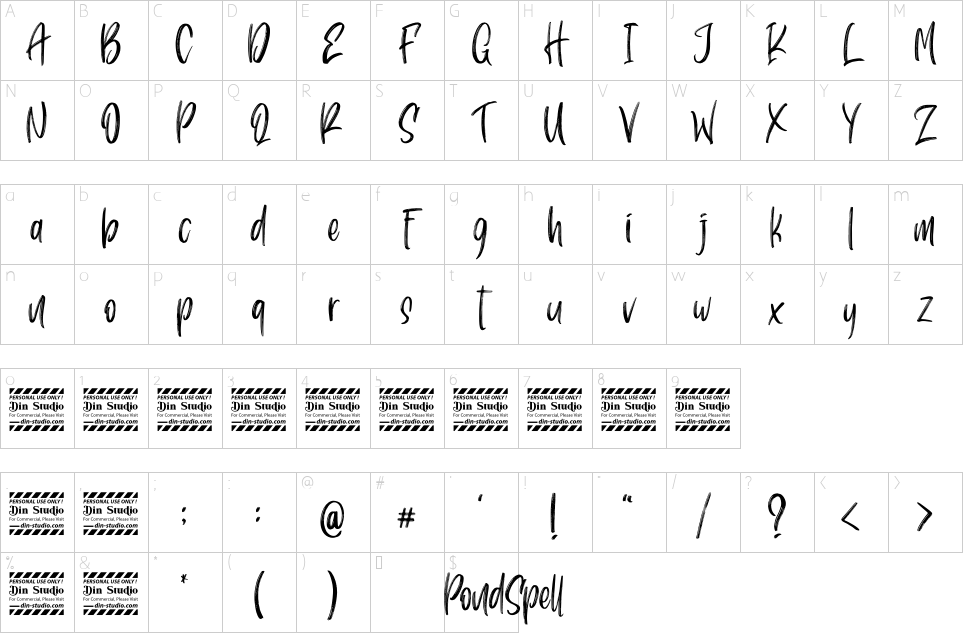
Descubra a beleza de Pondspell, uma fonte grátis disponível tanto para Windows quanto para Mac. Desenhada pelo Din Studio, Pondspell é mais do que um recurso para estilizar seu próximo projeto de design. Suas formas elegantes e sua tipografia cuidadosamente desenvolvida podem tornar qualquer trabalho em design de arte mais envolvente. Esta fonte oferece um toque único e inspirador, perfeito para aqueles que buscam uma adição fresca e versátil à sua coleção de fontes. Com um design cuidadosamente otimizado para diversos tamanhos e ambientes, Pondspell está pronta para ajudá-lo a criar designs de arte que realmente chamem a atenção. Com sua facilidade de uso e qualidade impecável, Pondspell é um investimento que valerá a pena. Experimente hoje e descubra por si mesmo por que essa fonte tem sido baixada mais de 2000 vezes.